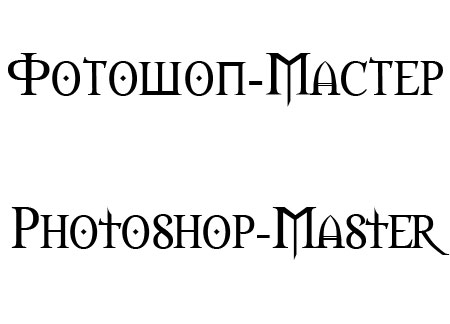
К сожалению шрифт не поддерживает кириллицу. Исправьте, пожалуйста, описание и смените раздел. Не вводите людей в заблеждение
у меня вместо русских букв квадратики((
Шрифт используется в World of Warcraft :)